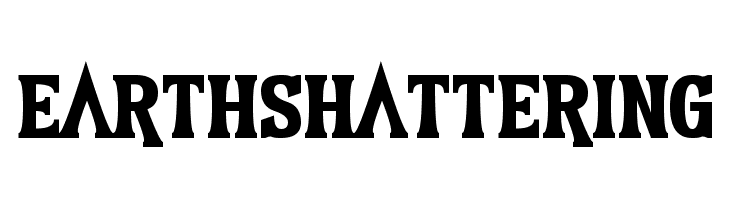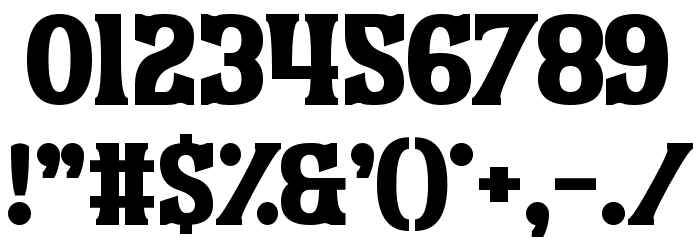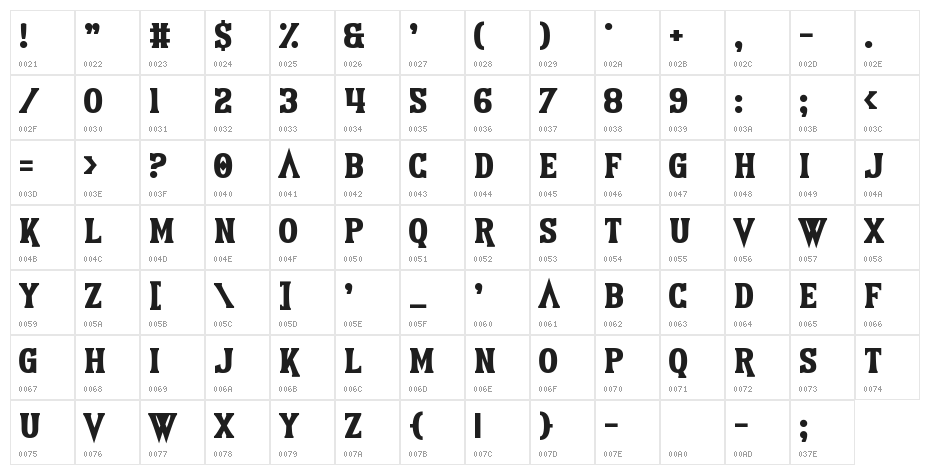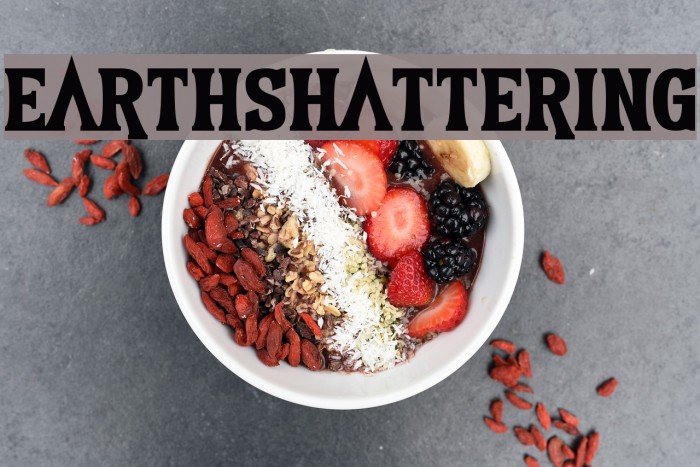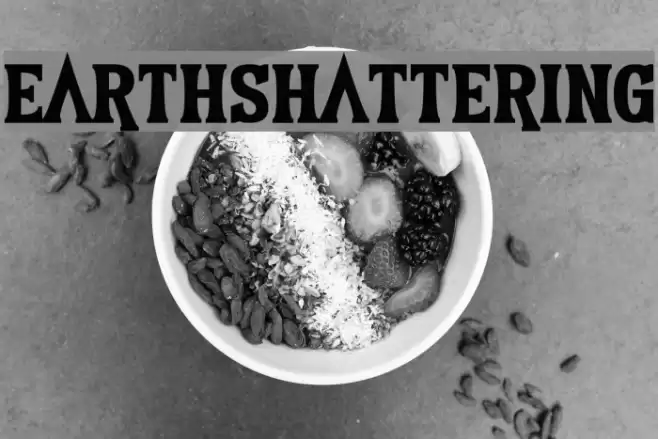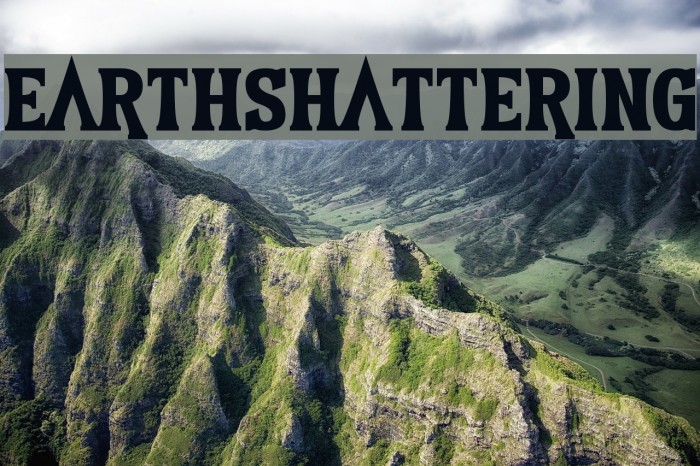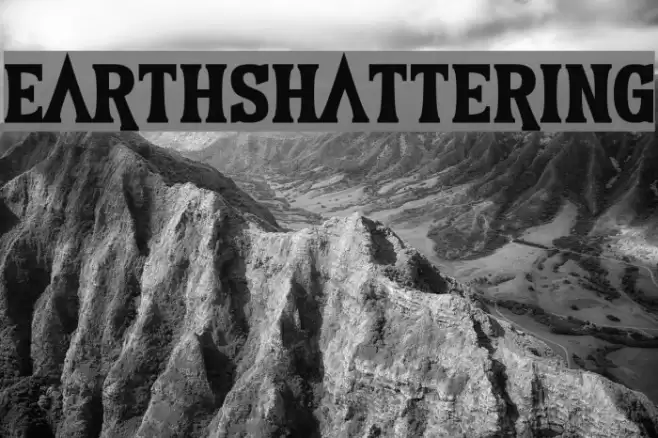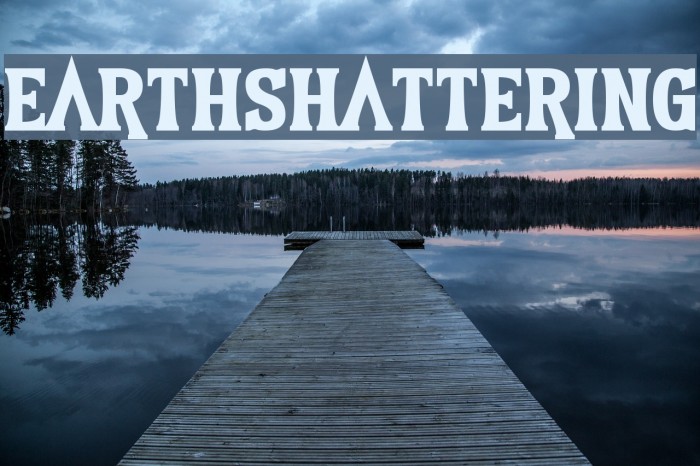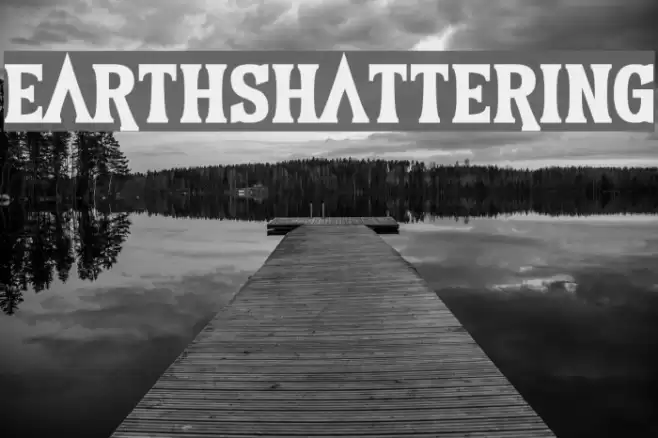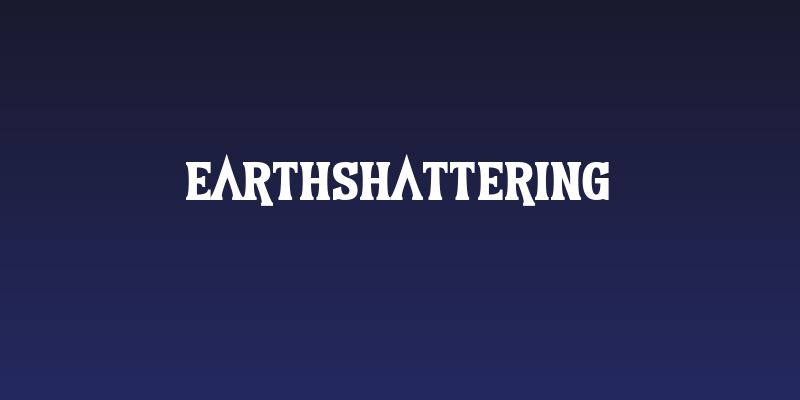
Earthshattering Font
✎ Serif
| おすすめプロジェクト | Ideal for use in posters, headlines, branding, and any project that requires a bold, attention-grabbing typeface. |